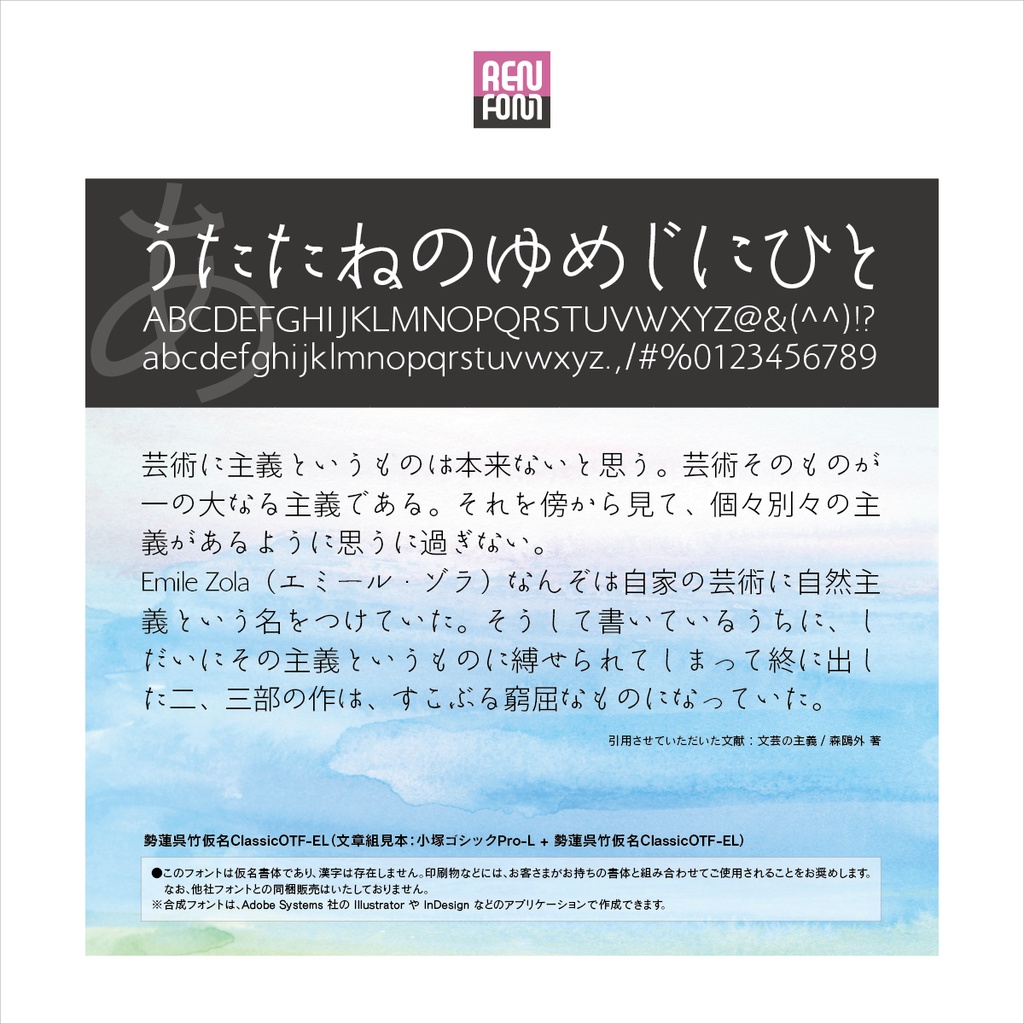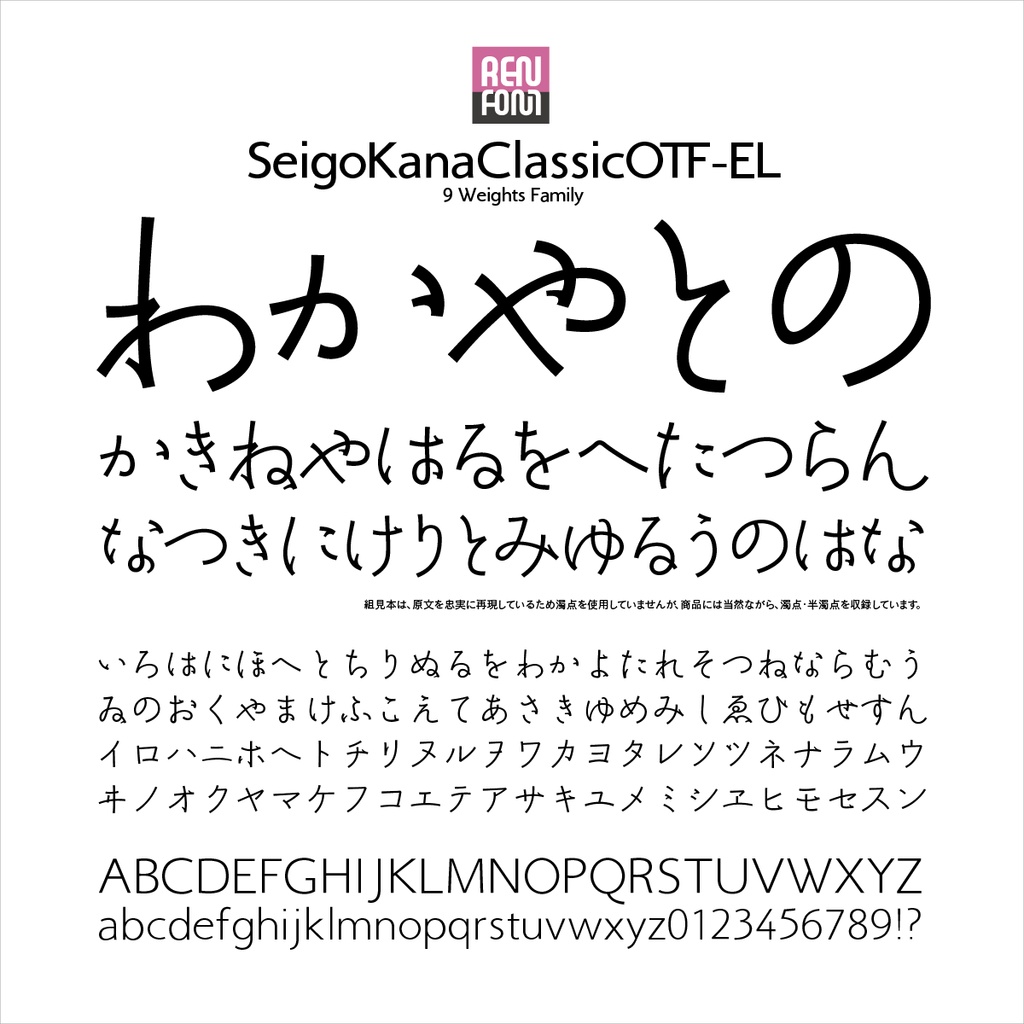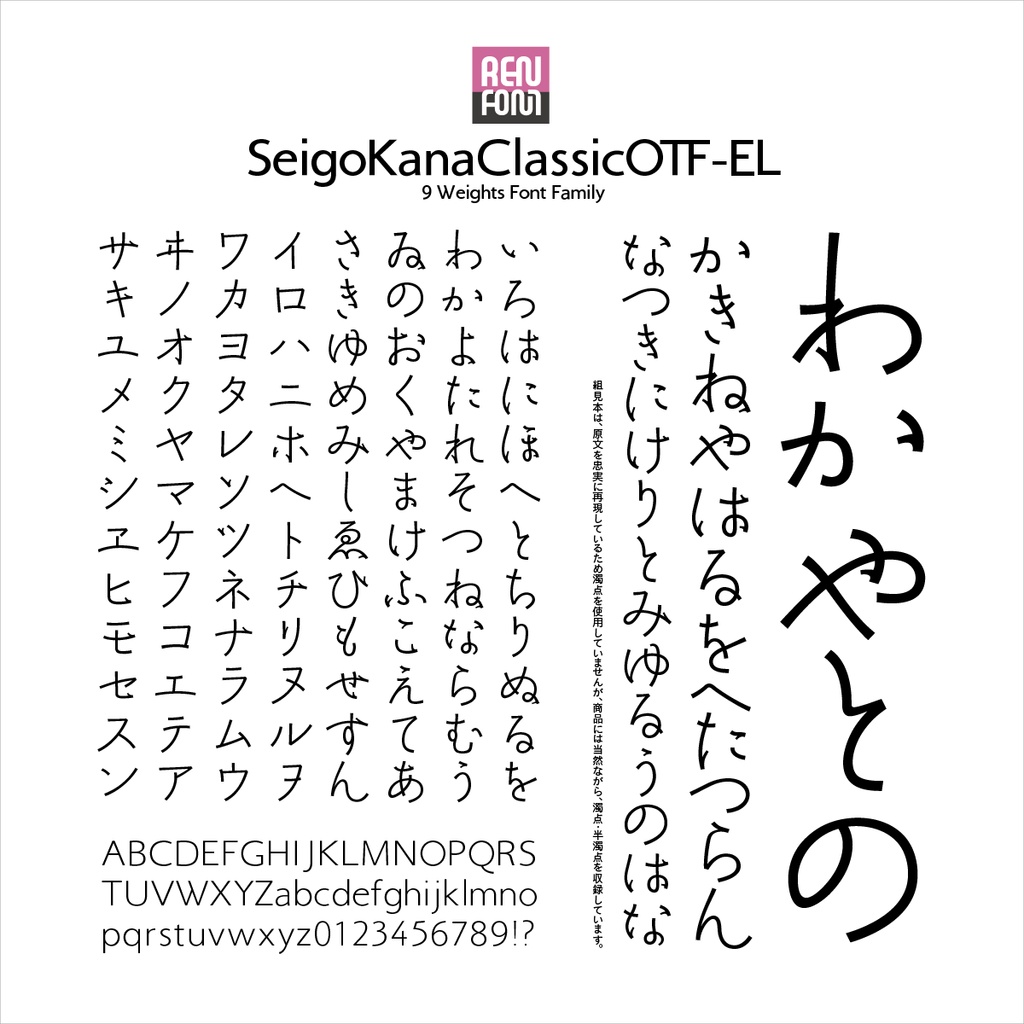
勢蓮呉竹トライアルEL
●ゴシックを感じさせない優雅さ 勢蓮呉竹トライアルEL / OpenType(試用版/フリーフォント)
ゴシックでありながら和の情緒、清潔さを合わせ持つ。
勢蓮呉竹仮名Classicファミリーの各書体は、2001年度特定非営利活動法人日本タイポグラフィ協会により開催された「日本タイポグラフィ年鑑2001」コンテストの書体部門入選作「勢蓮明朝-M」をブラッシュアップした骨格にゴシックの特徴を加えて、多ウェイト化したものです。 この書体は、当社タイプデザイナー金井和夫の普段使いの文字をベースとした、明朝・行書・楷書の複雑なフォルムイメージを持っています。最細ウェイト「L(ライト)」から最太ウェイト「U(ウルトラ)」までの、合計9ウェイトで構成されています。また、オールドなイメージを残しつつも、その概念にとらわれず大仮名に設計してあるので、近代的な組版にも対応するマルチな性格を備えています。 ゴシックでありながら和の雰囲気、清潔さを兼ね備えています。文字の幅・高さを一定にするデジタルフォントの流れに逆らい、敢えて不揃いにすることで、組にリズムと軽やかさを表現します。細めのウェイトでは華奢さを、太めのウェイトでは大胆さを与えます。そして、全ウェイトに共通する文字の流れの流麗さが高級感を演出します。
勢蓮呉竹トライアルELについて
勢蓮呉竹仮名Classicファミリーにご興味をお持ちいただき、ありがとうございます。 勢蓮呉竹仮名Classicファミリーは、日本タイポグラフィ協会2001年度年鑑受賞作品「勢蓮明朝-M」をブラッシュアップした骨格にゴシックの特徴を加えて、多ウェイト化したものです。 本書体は、計9ウェイトの中で、EL(エクストラライト)ウェイトの一部文字をお試しいただけるものです。 勢蓮呉竹仮名Classicファミリーは、以下の9ウェイトから成り立っています。
収録文字